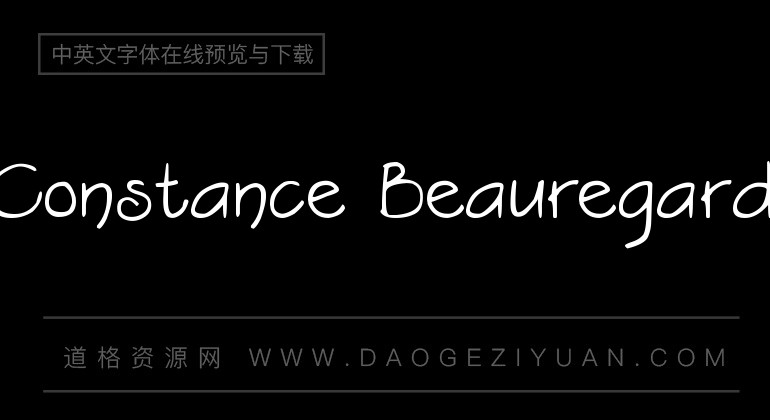
DJB Constance Beauregard Font
DJB Constance Beauregard Font 是一种手写字体,由美国设计师Darcy Baldwin创建。这种字体具有独特的风格,看起来像是在纸上用钢笔写出的字体。它的外观非常个性化,适合用于各种文本设计,例如贺卡、海报、手写信件等等。 这种字体具有良好的可读性,因为每个字母都是清晰可辨的。它的设计风格轻松自然,让人感觉非常舒适,同时也非常适合用于印刷材料。 总的来说,DJB Constance Beauregard Font 是一种充满个性化和艺术感的字体,适合用于各种文本设计。
DJB Constance Beauregard Font是一款非常不错的手写艺术字体,具有很好的视觉感,适合于文化类的宣传设计、商业类品牌的广告和产品包装设计以及个性化文字排版等较多场景。